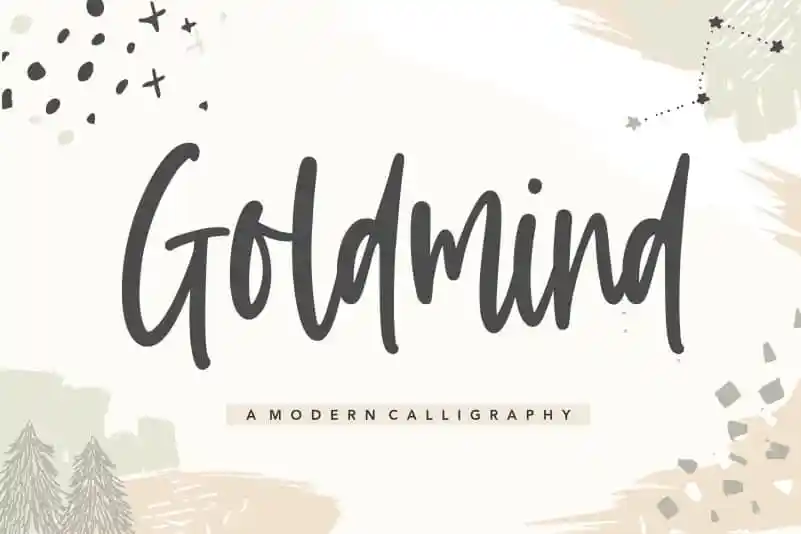
Goldmind Modern Calligraphy Font – Download Grátis
A Goldmind Modern Calligraphy Font é perfeita para criar texturas elegantes e sutis que se destacam nos ambientes mais diversos. Seja ela a sua escolha para embalagens de produtos, projetos de marca, revistas, redes sociais, casamentos ou simplesmente uma maneira criativa de expressar palavras acima do fundo. Esta fonte artesanal traz um toque refinado e único aos seus trabalhos gráficos, tornando-o ainda mais chamativo para o público que busca destaque em um mundo onde a atenção seco pode ser desafiada. Com ela, você pode criar design visual impressionantes que não apenas compõem a aparência de seu projeto, mas também sua essência.